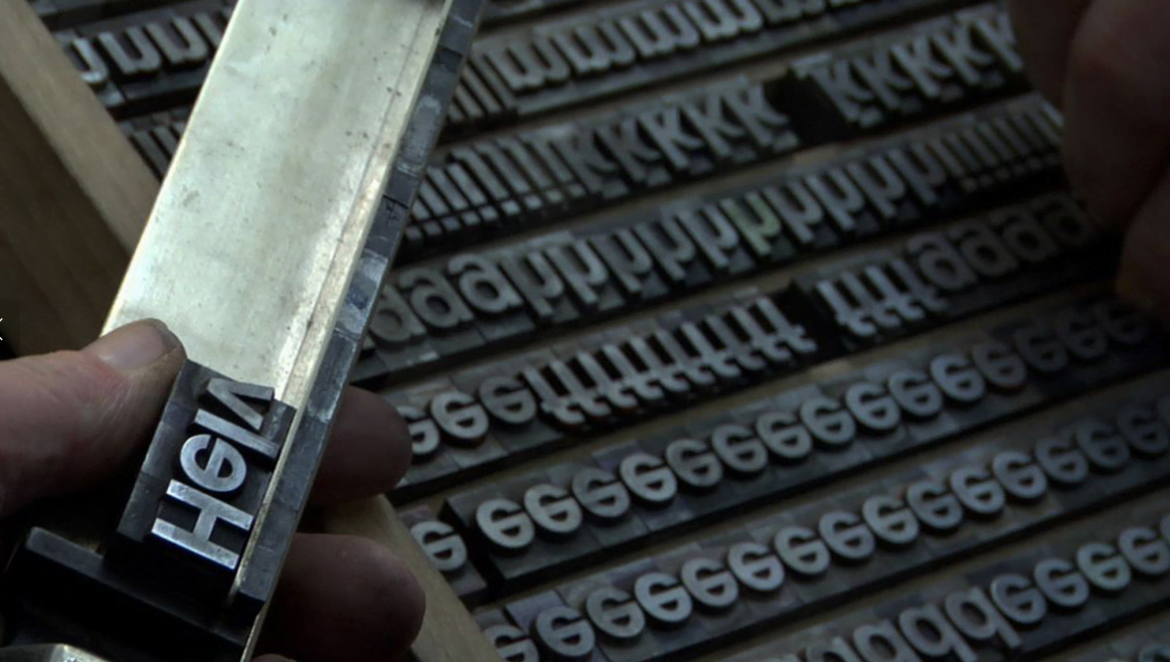
«Helvetica» la tipografía más popular
Helvetica
La tipografía forma parte de nuestras vidas, no solo la encontramos en los diseños gráficos y en la publicidad, sino que también en el nuestro día a día. Por ejemplo, la podemos encontrar en los carteles, en las Series de TV, en los medicamentos, en las indicaciones o en una simple tarjeta de autobús.
Pero… ¿Sabías que la tipografía Helvetica es la que te encontrarás en la mayoría de los títulos que te rodean?
helvetica
Y es que la Helvetica no es solo una de las tipografías más usadas desde su creación en 1957, también es una de las más influyentes en el diseño gráfico de los últimos 60 años.
Esta tipografía y sus variaciones se han usado en los logotipos de las series más exitosas del momento, ¿lo sabías?
Imaginaros la importancia de esta letra, que se ha hecho un documental sobre ella y su uso mundial. Una vez lo hayas visto, no podrás parar de mirar a tu alrededor para buscar este tipo de letra. Aquí podrás ver un avance:
El tipo de letra como parte esencial de nuestra comunicación visual, no solo influye en el diseño gráfico y la publicidad, sino que también se encuentra arraigada en nuestro día a día, presente en carteles, series de televisión, medicamentos, indicaciones y hasta en las tarjetas de autobús. Es interesante destacar que la omnipresencia de la tipografía Helvetica en una variedad de títulos que nos rodean resalta su importancia y su impacto en la estética visual contemporánea.